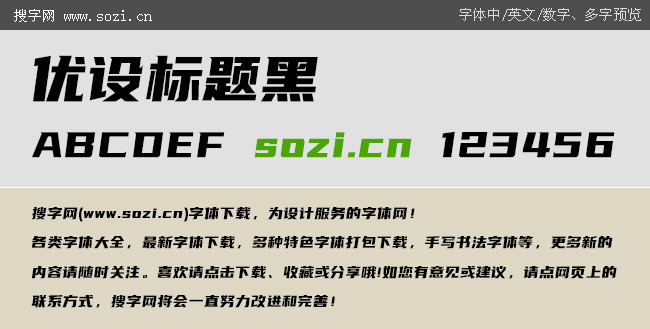
優(yōu)設(shè)標(biāo)題黑
搜字網(wǎng)給大家提供一款優(yōu)設(shè)標(biāo)題黑中文字體下載,優(yōu)設(shè)標(biāo)題黑是優(yōu)設(shè)最新出品的一款可以商用的字體,字體線條粗細(xì)適中,字形帶有傾斜效果,具有很好的視覺感,適合應(yīng)用于藝術(shù)設(shè)計、平面宣傳設(shè)計、網(wǎng)頁設(shè)計等領(lǐng)域。